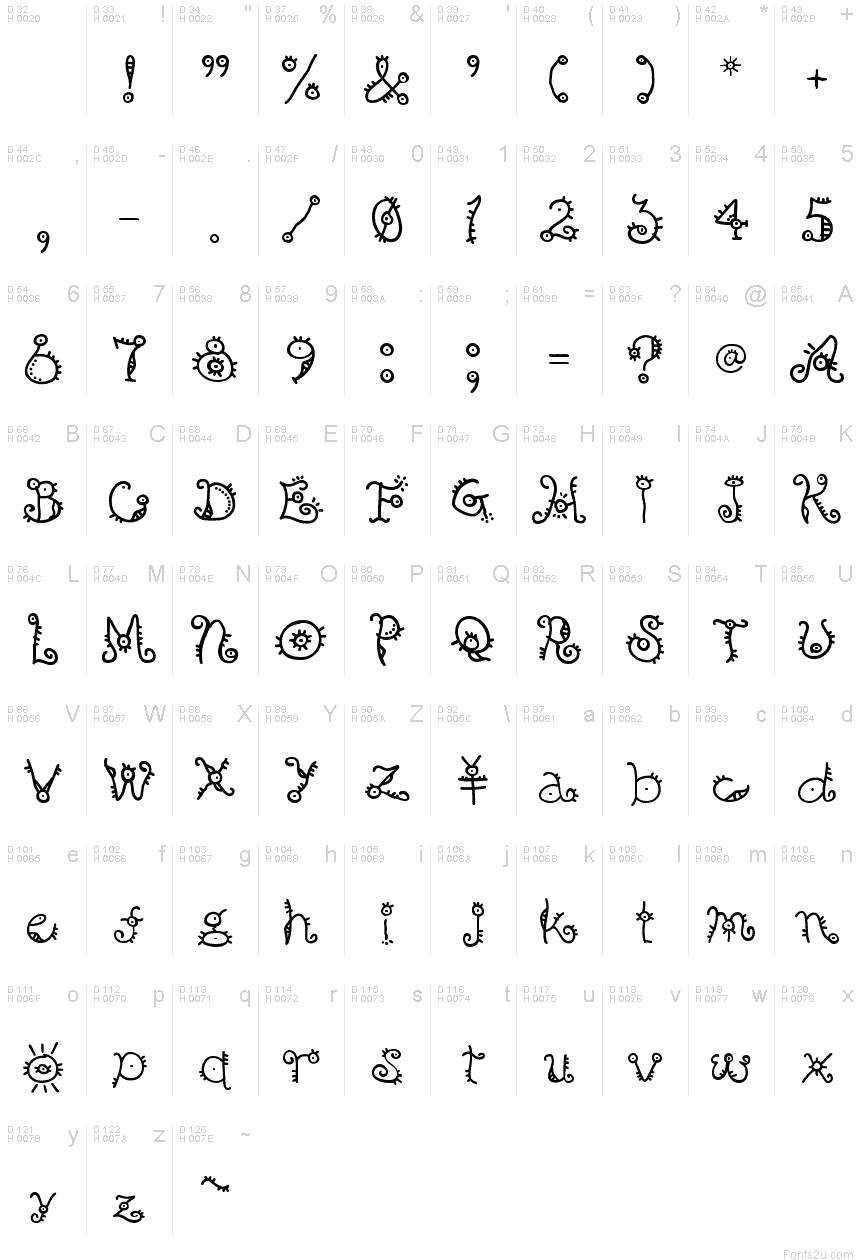
B Surfers Plane autorstwa Tohru Fukushimy to darmowy, kreskówkowy krój pisma, który zmienia każdą literę w małego stwora. Rodzina B Surfers wygina się i kręci za sprawą atramentowych, ręcznie rysowanych pętli, kolców i szeroko otwartych „oczu”, które zdobią znaki, nadając tekstowi buzującą, lekko chaotyczną energię. Wygląda jak bazgroł, który właśnie ożył – jest zabawny, dziwaczny i pełen życia.
Dzięki B Surfers Plane Twoje nagłówki nie tylko przemawiają, one wręcz wiją się na stronie. Ten darmowy font świetnie sprawdzi się na plakatach koncertowych, w fanzinach, logotypach zespołów, na ulotkach na Halloween lub imprezy tematyczne, w grafikach na deskorolki oraz jako wyrazista miniatura w mediach społecznościowych czy na YouTube. Stosuj duże rozmiary, aby drobne kolce i zawijasy pozostały ostre, a do tekstu głównego dobierz prosty, kompaktowy krój bezszeryfowy, aby dzikie litery mogły grać główną rolę.